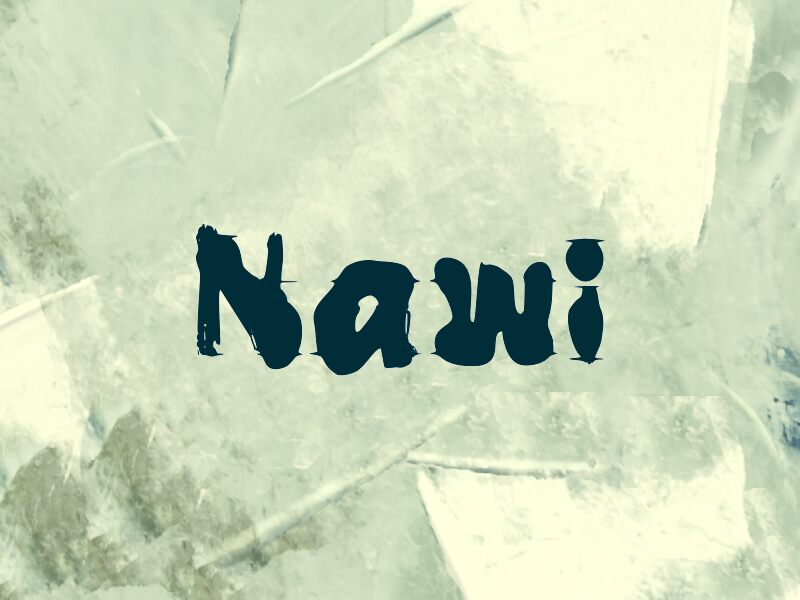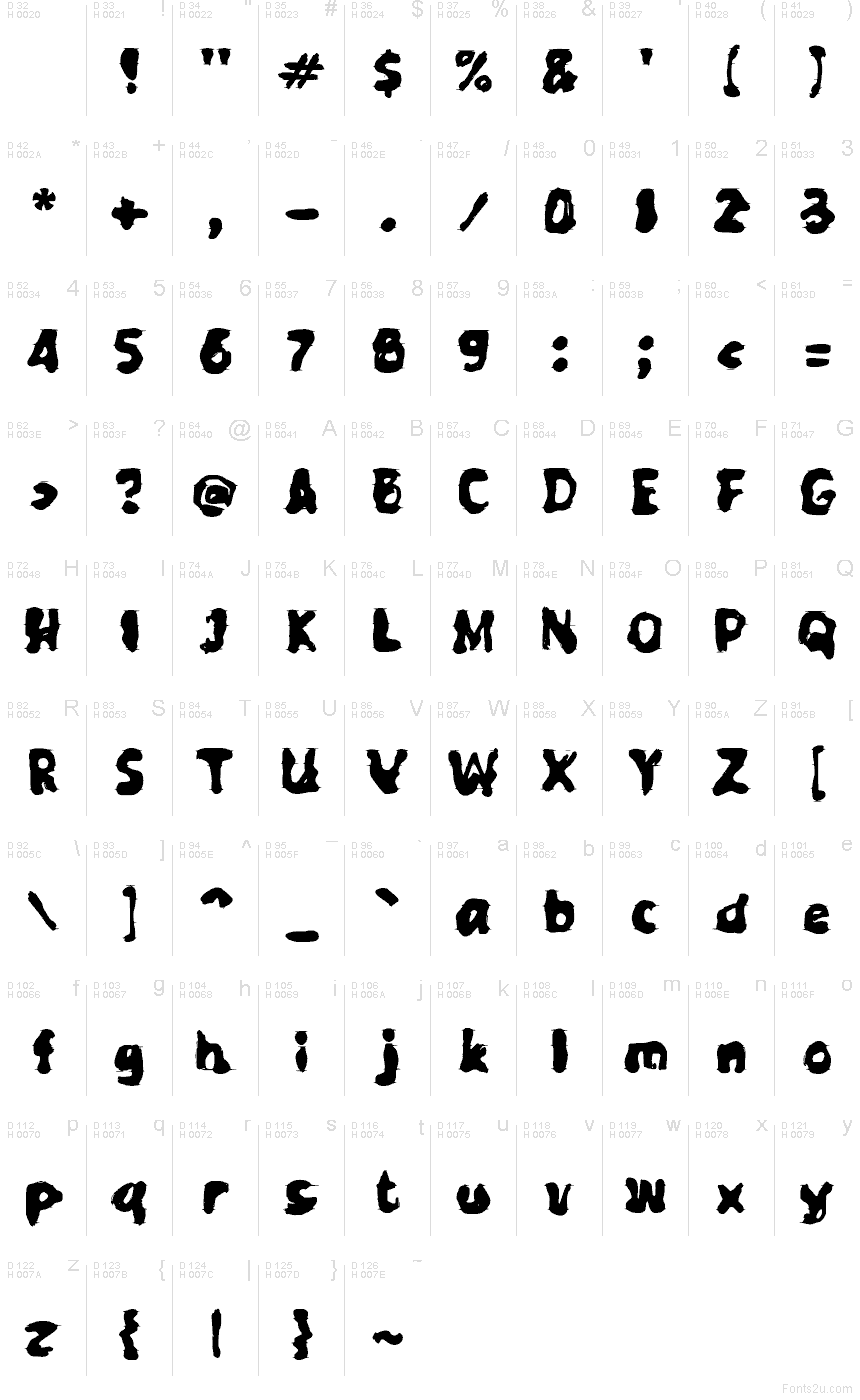
Nawi от Wep — это бесплатный brush-шрифт с сырым, «ручным» характером. Буквы выглядят плотными, влажными и слегка бунтарскими: тяжелые кривые, сжатые соединения и неровные края делают этот шрифт скорее похожим на быстро нарисованную вывеску, чем на аккуратный цифровой набор.
Эта энергия отлично подходит для заголовков плакатов, оформления музыкальных релизов, инди-упаковки, обложек зинов и брендинга кофеен — везде, где требуется создать атмосферу живого, рукописного творчества. Шрифт также хорош для коротких заголовков, так как массивные мазки кистью и неровный ритм придают даже нескольким буквам сильный и неформальный вид.
Nawi